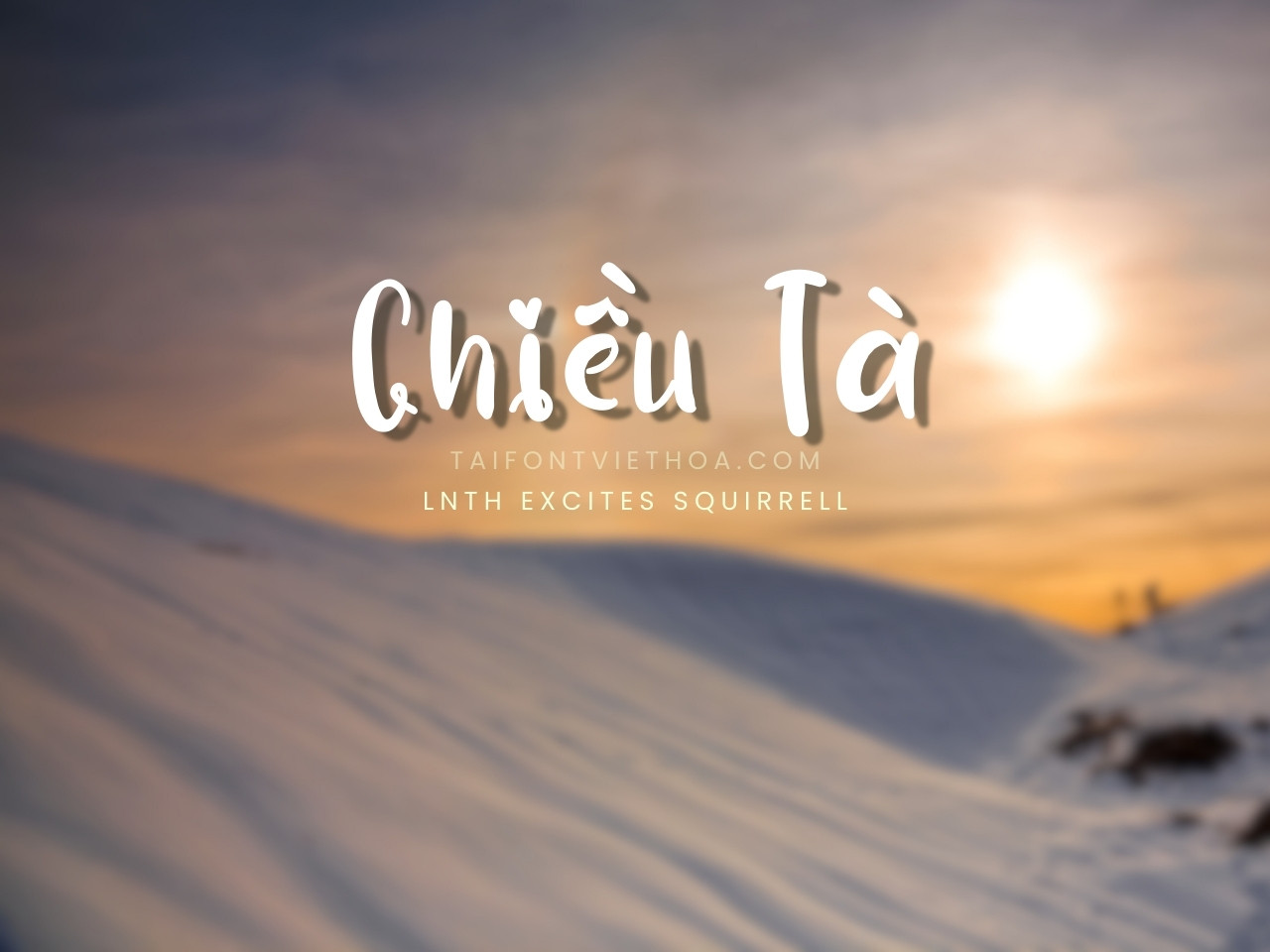
Giới thiệu về font LNTH Excites Squirrell – Viết tay hoạt hình đầy vui nhộn và sáng tạo
LNTH Excites Squirrell là phiên bản Việt hóa từ font viết tay sáng tạo “Excites Squirrell” của Fhammadiq Std – một nhà thiết kế nổi bật trong việc tạo ra những kiểu chữ mang tính hoạt hình và biểu cảm cao. Font mang nét viết tay ngộ nghĩnh, vui tươi, thích hợp cho các thiết kế truyền cảm hứng và giải trí. Phiên bản Việt hóa được thực hiện bởi Tuỳn Pucca, hỗ trợ đầy đủ tiếng Việt và hơn 60 ngôn ngữ khác, giúp người dùng dễ dàng sử dụng trong các dự án toàn cầu mà vẫn giữ được nét cá tính đặc trưng.
Đặc điểm thiết kế và ứng dụng của LNTH Excites Squirrell
LNTH Excites Squirrell mang phong cách handwritten hoạt hình – các đường nét mềm mại, biến tấu linh hoạt giữa độ dày và nét cong. Mỗi ký tự đều có biểu cảm riêng, tạo hiệu ứng sống động như nét vẽ tay thực thụ. Font này không chỉ đóng vai trò truyền tải nội dung, mà còn là một phần trong nhận diện thị giác sáng tạo của thiết kế.
Font phù hợp cho các ứng dụng như: poster lớp học, thiệp sinh nhật, bao bì snack, banner trò chơi, tiêu đề video hoạt hình hoặc blog giáo dục cho trẻ nhỏ. Ngành nghề phù hợp gồm: giáo dục, giải trí thiếu nhi, công nghệ sáng tạo, quảng cáo sản phẩm vui nhộn hoặc các thương hiệu hướng đến đối tượng trẻ tuổi.